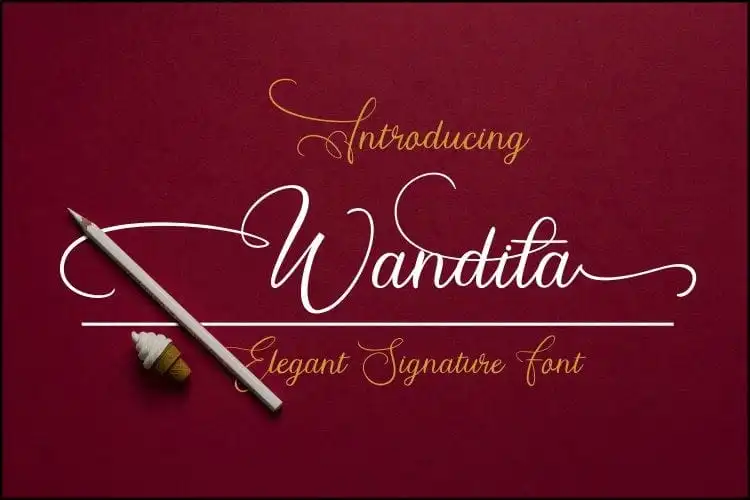
Wandita Script Font – Download Grátis
A Wandita Script é uma fonte moderna que lembra a elegância dos traços humanizados, ideal para quem busca trazer sofisticação e estilo ao seu trabalho design. Com um fluxo natural e elegante, esta coleção de scripts perfeita para personal branding se destaca como uma escolha versátil para diversas aplicações. Ela atende desde o branding pessoal até as maiores iniciativas de marketing, seja em cartões de convidados ou campanhas publicitárias. Composta por texturas e formas sofisticadas que parecem ter sido desenhadas por uma artesã, a Wandita Script oferece um toque refinado às suas criações, tornando-a uma excelente opção para aqueles que buscam deixar seu design ainda mais expressivo.